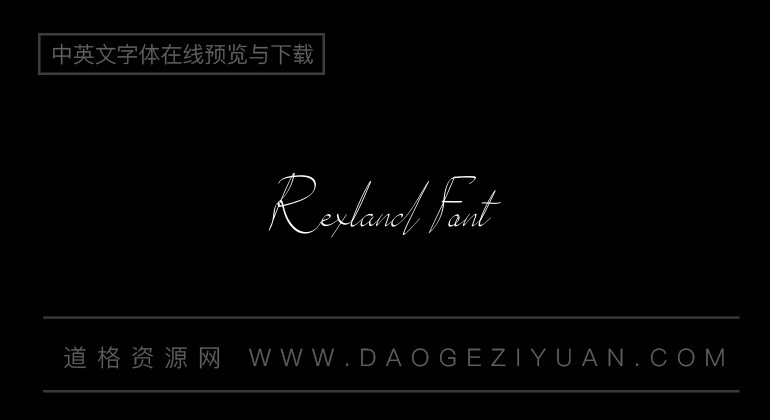
Rexland Font
Rexland Font是一种现代、优雅和流畅的字体,由字体设计师Tama Putra设计。这种字体有许多独特的特点,首先是它的笔画非常流畅,其次是它的字形非常简洁,这使得它非常适合用于许多不同类型的设计项目。 Rexland Font拥有多种字重,从轻到黑,可以根据需要进行选择。此外,它还包括了一系列的字形变体和连字,这使得它非常适合用于设计标志、海报、广告、印刷品和数字媒体等各种项目。 总的来说,Rexland Font是一种非常精美和实用的字体,它可以为任何设计项目增添一份现代感和优雅感。
Rexland Font是一款非常不错的手写艺术字体,具有很好的视觉感,适合于文化类的宣传设计、商业类品牌的广告和产品包装设计以及个性化文字排版等较多场景。